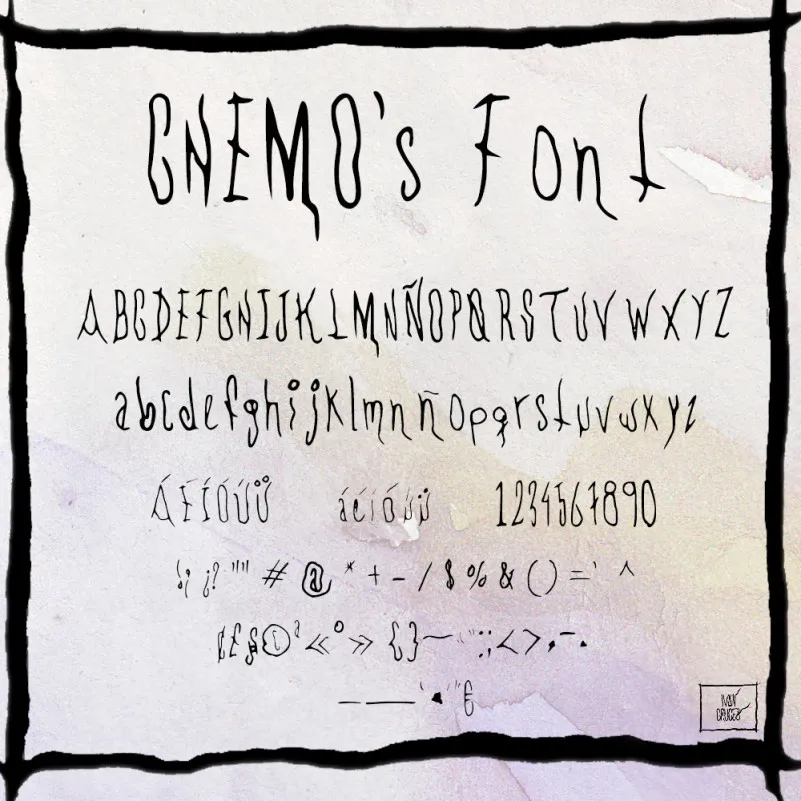
CHEMOs Font – Download Grátis
A CHEMOs Font é uma deliciosa mistura de caligrafia natural que surgiu dos desenhos delicados do artista Hamilton em suas obras de acuarela. Inspirado na mesma linha no qual ele cria seus desenhos acuarelas, a CHEMOs oferece uma experiência visual única e envolvente. Com traços fluidos e cores vivas que se assemelham às linhas delicadas da pintura acrílica de Hamilton, esta fonte é perfeita para aqueles que buscam um toque de natureza em suas criações digitais. A CHEMOs tem uma presença poderosa sem ser excessiva, combinando a delicadeza e leveza das obras pictóricas do artista com uma textura cuidadosamente pensada para criar um efeito envolvente no seu design digital. Uma excelente escolha para designers que valorizam a combinação de arte natural e tecnologia na sua obra.